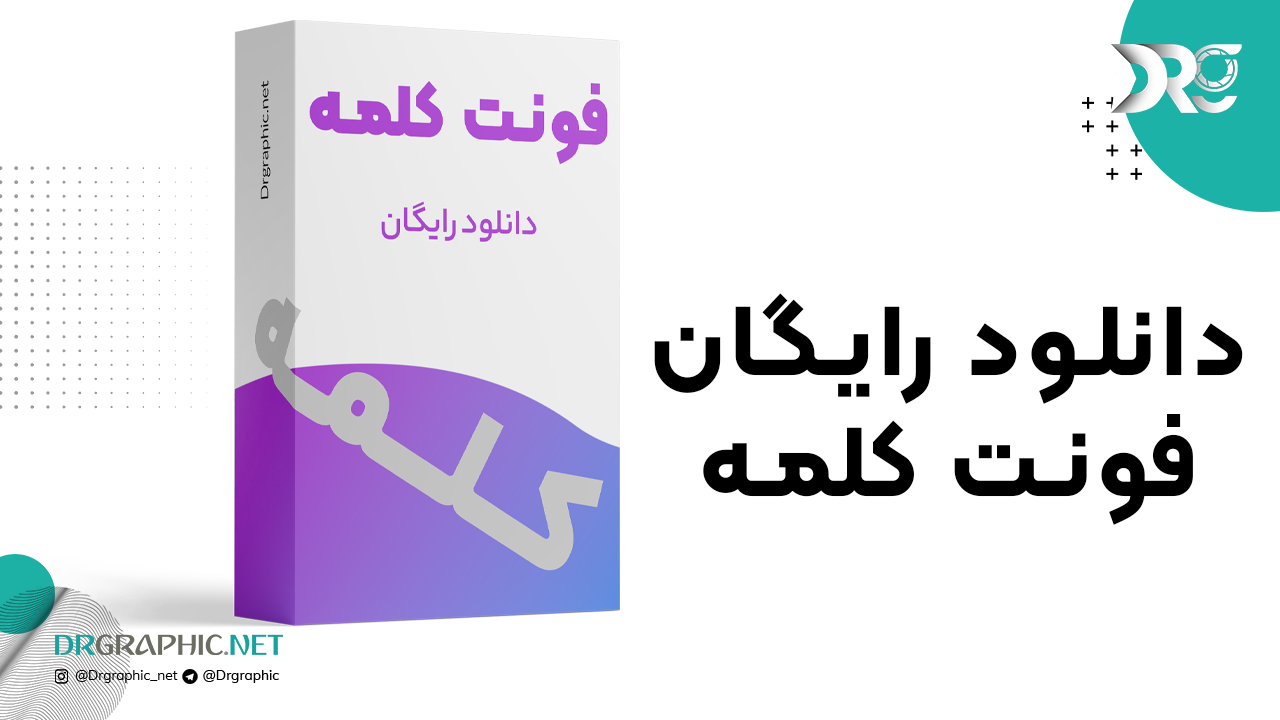
فونت کلمه یکی از زیباترین فونت های فارسی است که ساختاری منظم و هندسی دارد، ساختار این فونت شسته و رفته است و هماهنگی بسیار بالایی با فونت های انگلیسی دارد. فونت کلمه انرژی و پویایی خاصی دارد که بیشتر در کارهای تبلیغاتی استفاده میشود و امروزه بیشتر کسب و کارها و استارت آپ های خلاق از این فونت استفاده می کنند.
فونت کلمه یک خانواده کامل است که ۹ وزن دارد. از خیلی نازک تا سیاه تنوع کاملی از ضخامت و تیرگی را در اختیار شما قرار میدهد.
کلمه در بسته حرفهای خود، ۹ وزن و در بسته افتصادی ۴ وزن استاندارد را داراست که برای کاربردهای متنوع – از صنعت چاپ تا فضاهای مجازی – درنظر گرفته شده است. خانواده فونت پیدا برای استفاده در فضاهای وب نیز بهینهسازی شده است و فایلهای مورد نیاز در کنار فایلهای اصلی قرار داده شده است.
فونت کلمه علاوه بر زبان فارسی از زبانهای دیگر بر پایه این رسم خط پشتیبانی میکند. پشتیبانی این قلم شامل زبان عربی، اردو و کردی است که علاوه بر حروف مشترک، حروفی که تفاوت جزئی دارند را نیز برای هر زبان پشتیبانی میکند. حروفی مانند «ك، ي، ة، ؤ، ئ» در عربی که تفاوت جزئی دارند یا حروف «ﮧ، ﮩ، ے» در اردو پیاده سازی شده است.